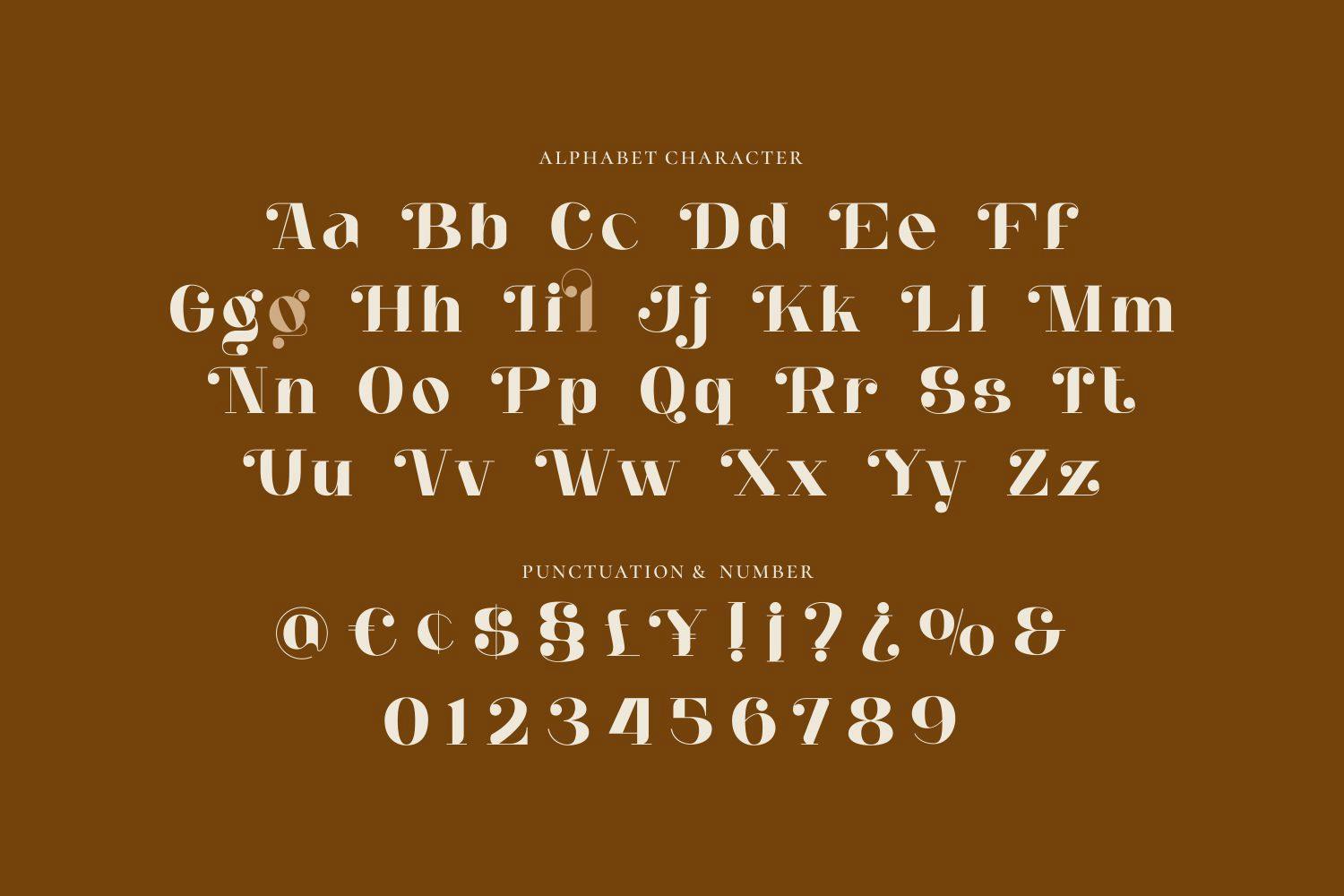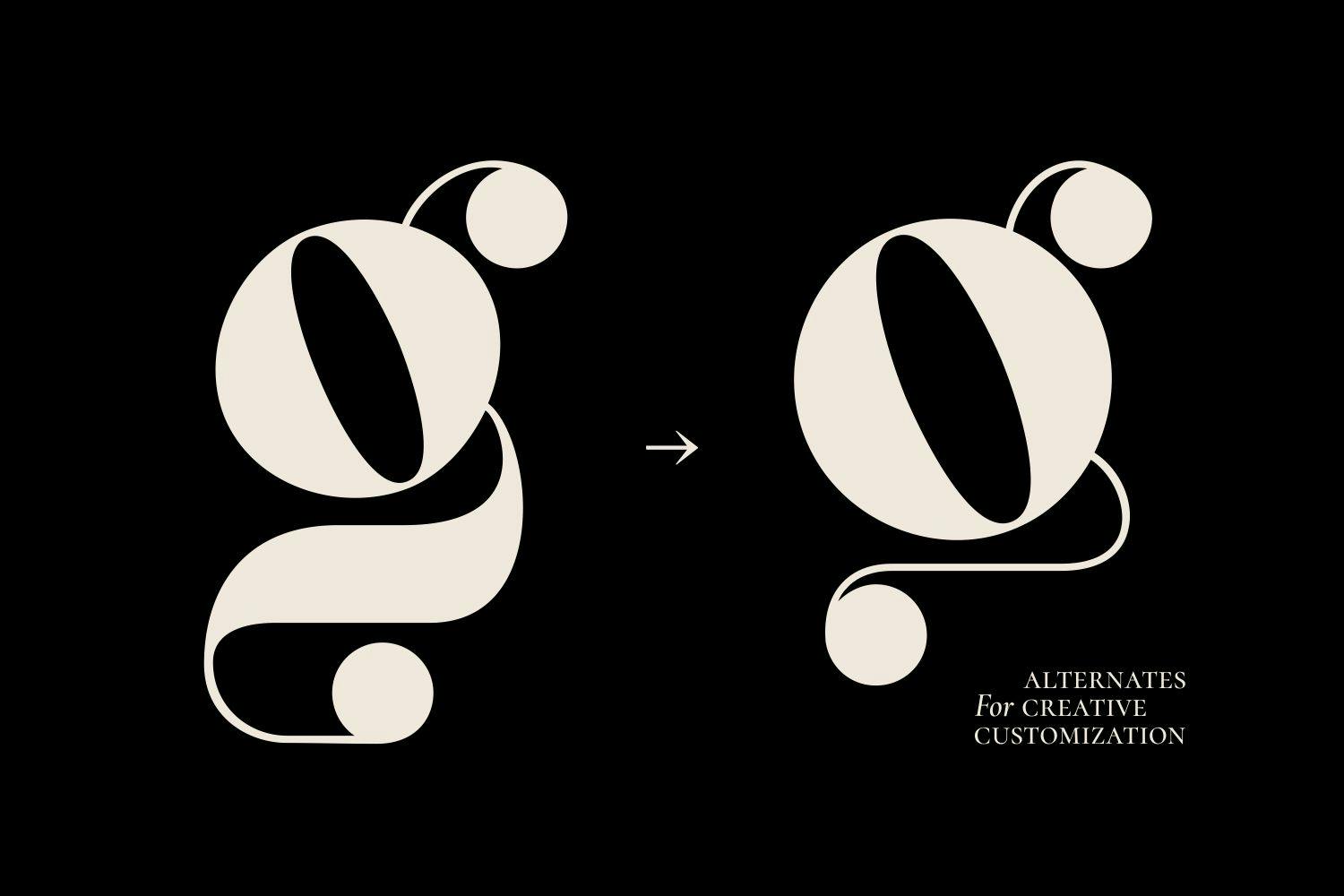
فونت Bolgek یک فونت لوکس با ظاهری شکیل، منحنیهای نرم و لیگاتورهای زیبا است که کار شما را جذاب و واقعی جلوه میدهد.
این فونت چندمنظوره در اندازههای بزرگ و کوچک به خوبی عمل میکند. فونت Bolgek برای انواع پروژهها نظیر لوگو، دعوتنامه، برندینگ، مجله، عکاسی، کارت، بستهبندی محصولات، ماکتهای محصول، ماگ، نقلقولها، پوسترها، برچسبها، امضاها، نشریات، وبسایتها، هنر دکوی اجتماعی و بسیاری موارد دیگر مناسب است.